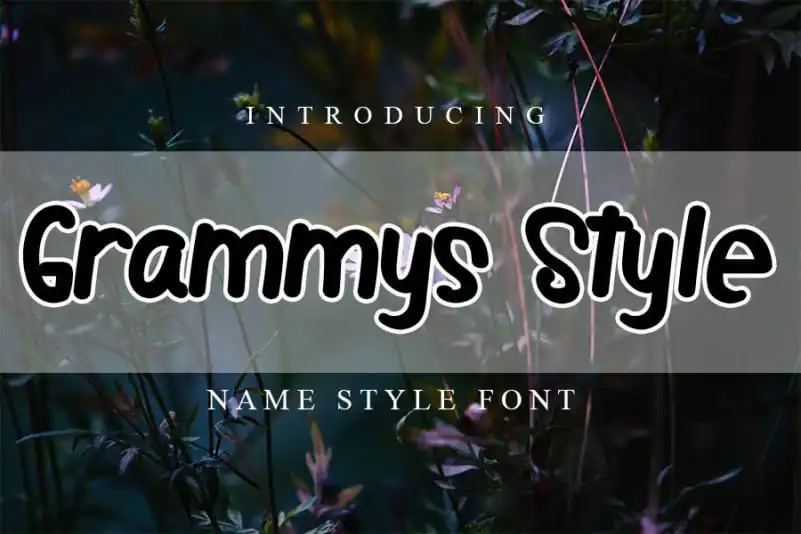
Grammys Style Script Font – Download Grátis
A Grammys Style Script Font é uma excelente escolha para designers que procuram adicionar um toque elegante ao seu trabalho sem se perder na superficialidade do estilo tradicionalmente chamado de script. Essa fonte mantém seus traços classicos, mas também reflete a contemporaneidade e o frescor atual. Suas características fluidas e alegres tornaram-a perfeita para um leque amplo de ideias criativas — desde assinaturas e títulos até materiais de papelaria. Ideal tanto para iniciantes quanto para profissionais experientes, ela é uma fonte versátil que não apenas complementa sua coleção atual, mas também traz um novo grau de expressividade ao seu trabalho.